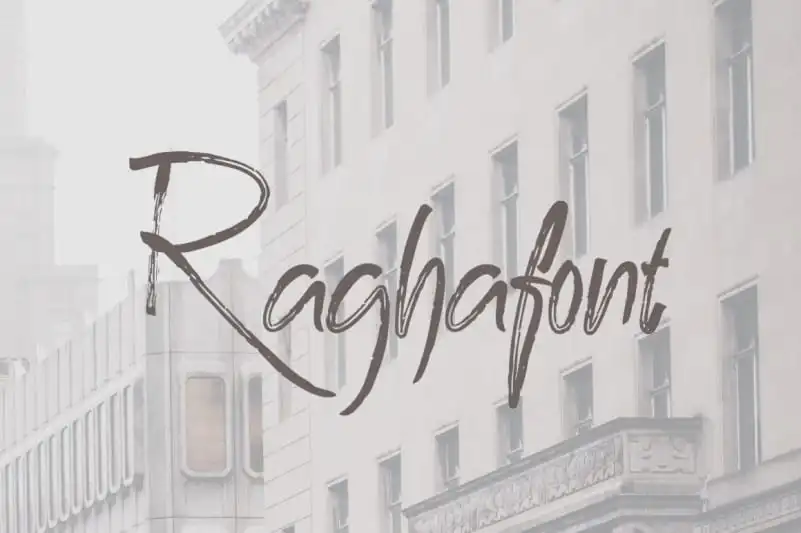
A Ragha Brush Font é uma maravilhosa escolha para quem busca dar um toque único a seus projetos digitais. Manufacturada pela Vaca Tama, esta fonte foi criada com a intenção de incorporar um estilo totalmente autêntico e natural ao seu design. Com uma aparência cheia de personalidade, que traz à tona os traços mais reais da escrita, ela mantém ainda assim um charme casual e descontraído que tornam suas criações distintas e originais. Ideal para quem busca adicionar um elemento diferenciado em seus projetos, seja ele gráficos, layouts ou até mesmo designs de aplicativos móveis, a Ragha Brush Font é perfeitamente adaptada para produzir resultados extraordinários. Perfecto!